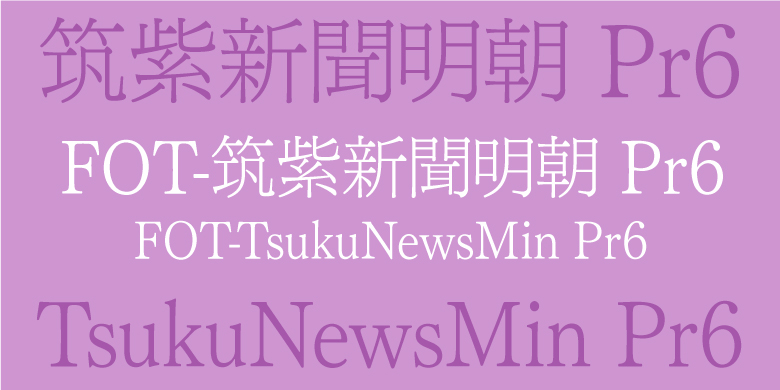
FOT-TsukuNewsMin Pr6
字体品牌: Fontworks 设计师:Fontworks 字体分类:宋体 字体属性:精品字 字符集:Unicode 发布时间: 2024
筑紫书体系列中的新闻明朝体以其锐利和柔软的设计为特点。特色是纵向80-90%缩小扁平的新闻风格,端正的骨架在文本页面上产生适当的紧张感,不仅适用于新闻,也适用于杂志等,能够营造出高品位感觉。